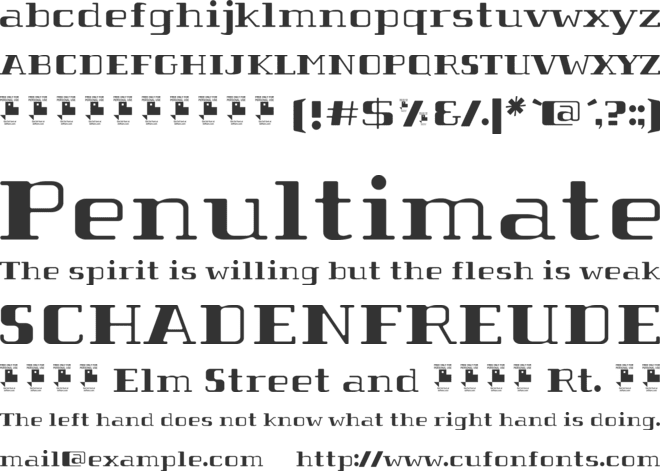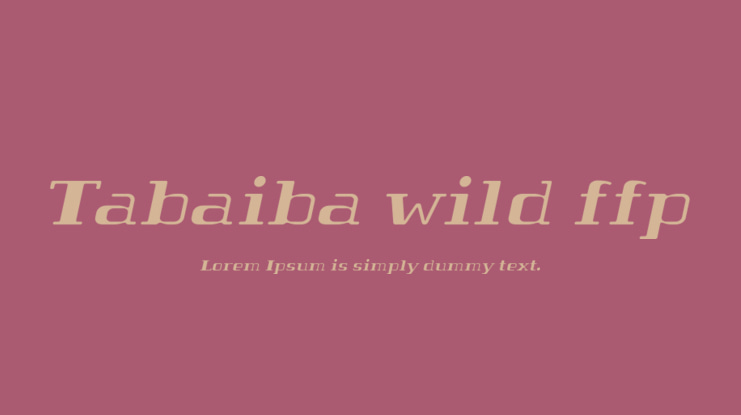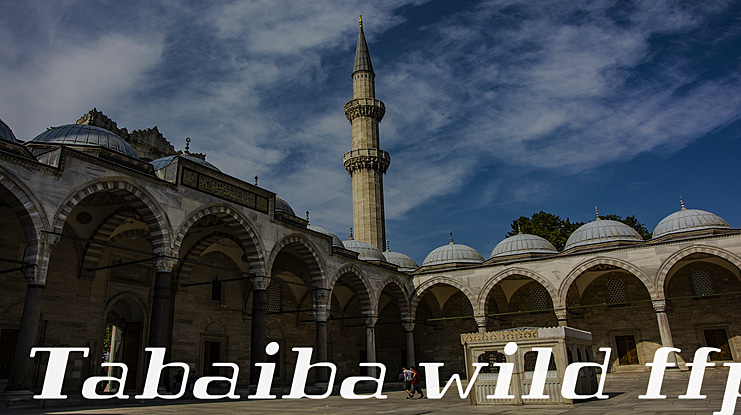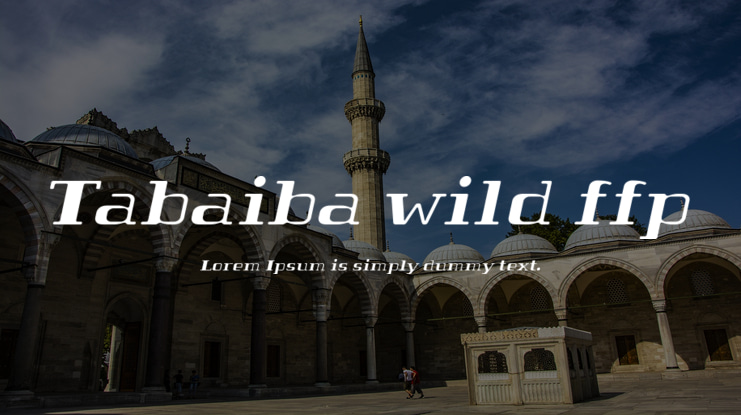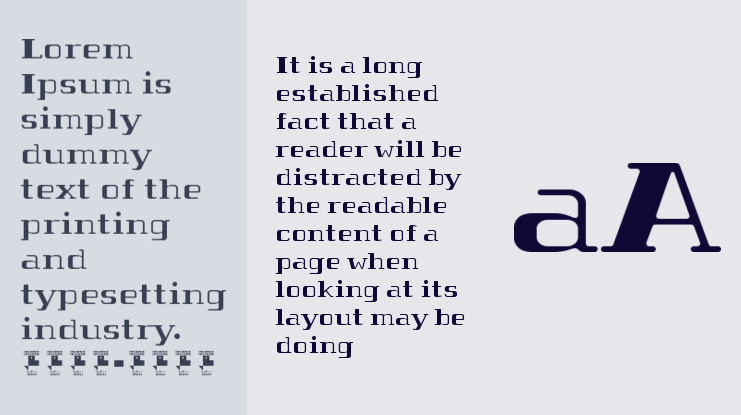
Tabaiba wild ffp Font Family
Tabaiba wild es una tipografía de proporciones cuadradas, slab serif redondeada con un estilo mezcla de tecno y modernismo, se comporta muy bien en párrafos de texto así como en titulares, el kerning lo he definido profusamente y añado la versión Itálica para uso en auto-edición.